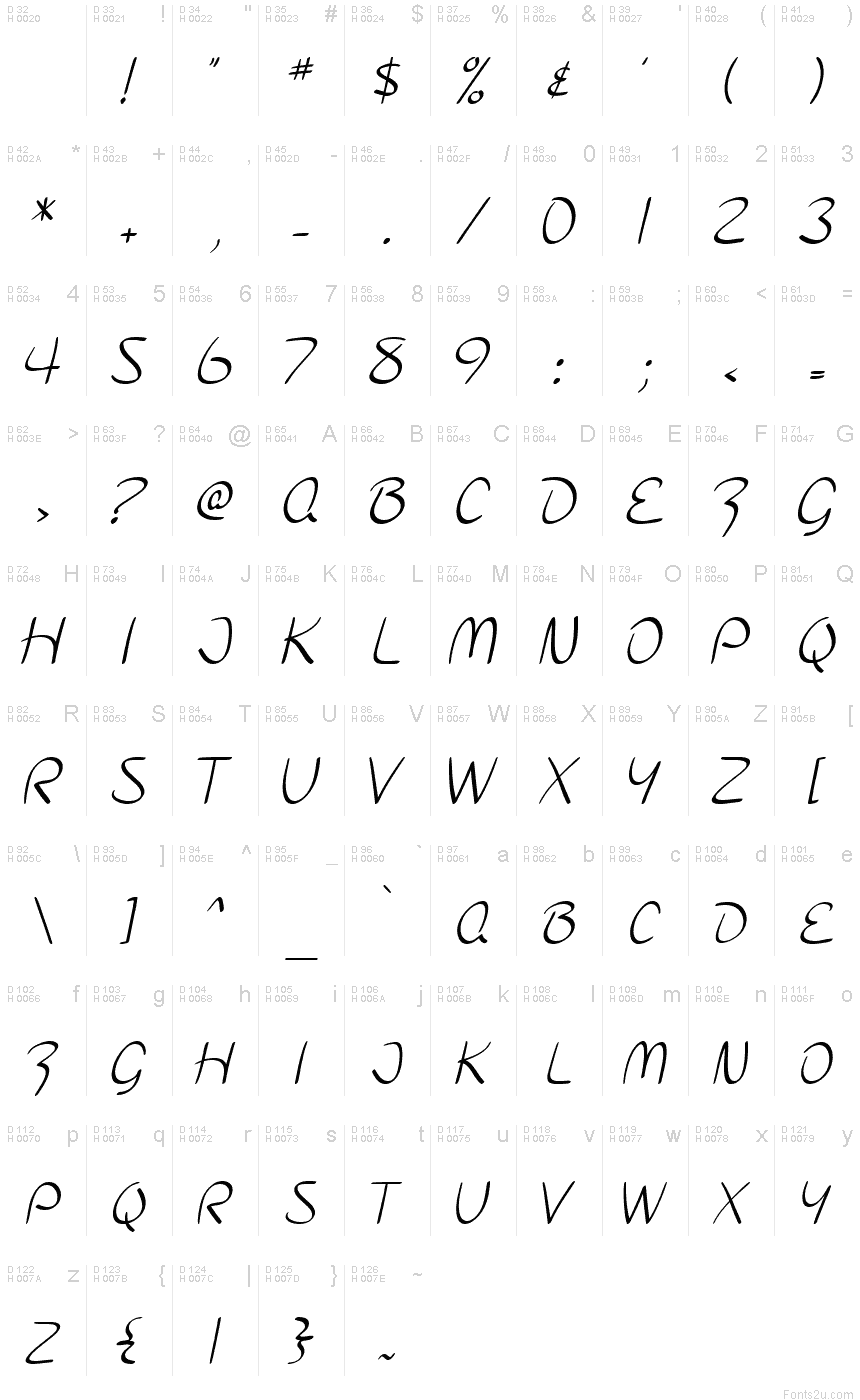
SF Burlington Script SC od ShyFoundry to bezpłatny krój pisma odręcznego, nawiązujący stylem do malowanych ręcznie szyldów z połowy XX wieku. Wielkie litery układają się w długie, sprężyste pociągnięcia, a zaokrąglone pętle i wysokie łuki sprawiają, że cały alfabet jest lekki, swobodny i bardziej modowy niż formalny.
Świetnie sprawdzi się w brandingu butików, menu kawiarni, opakowaniach kosmetyków, kartkach okolicznościowych i nagłówkach czasopism, wszędzie tam, gdzie darmowy font ma nadać całości charakter ręcznie nakreślonego podpisu. Ponieważ litery opierają się na szerokich gestach, a nie na drobnych detalach, najlepiej prezentują się w krótkich nagłówkach, tytułach i monogramach, gdzie te zapętlone wielkie litery mają odpowiednio dużo przestrzeni.
SF Burlington Script SC
ShyFoundry
Derek Vogelpohl